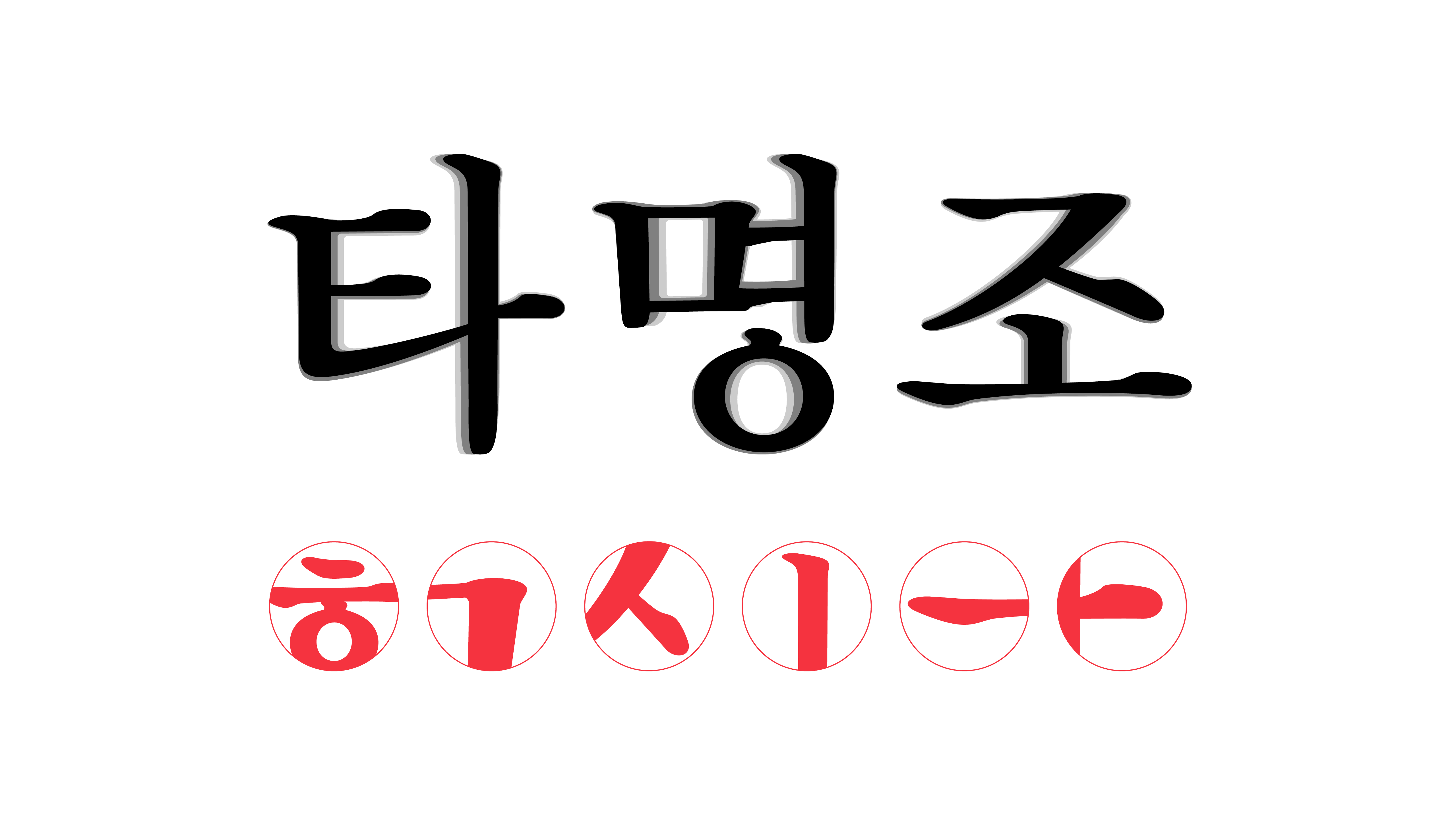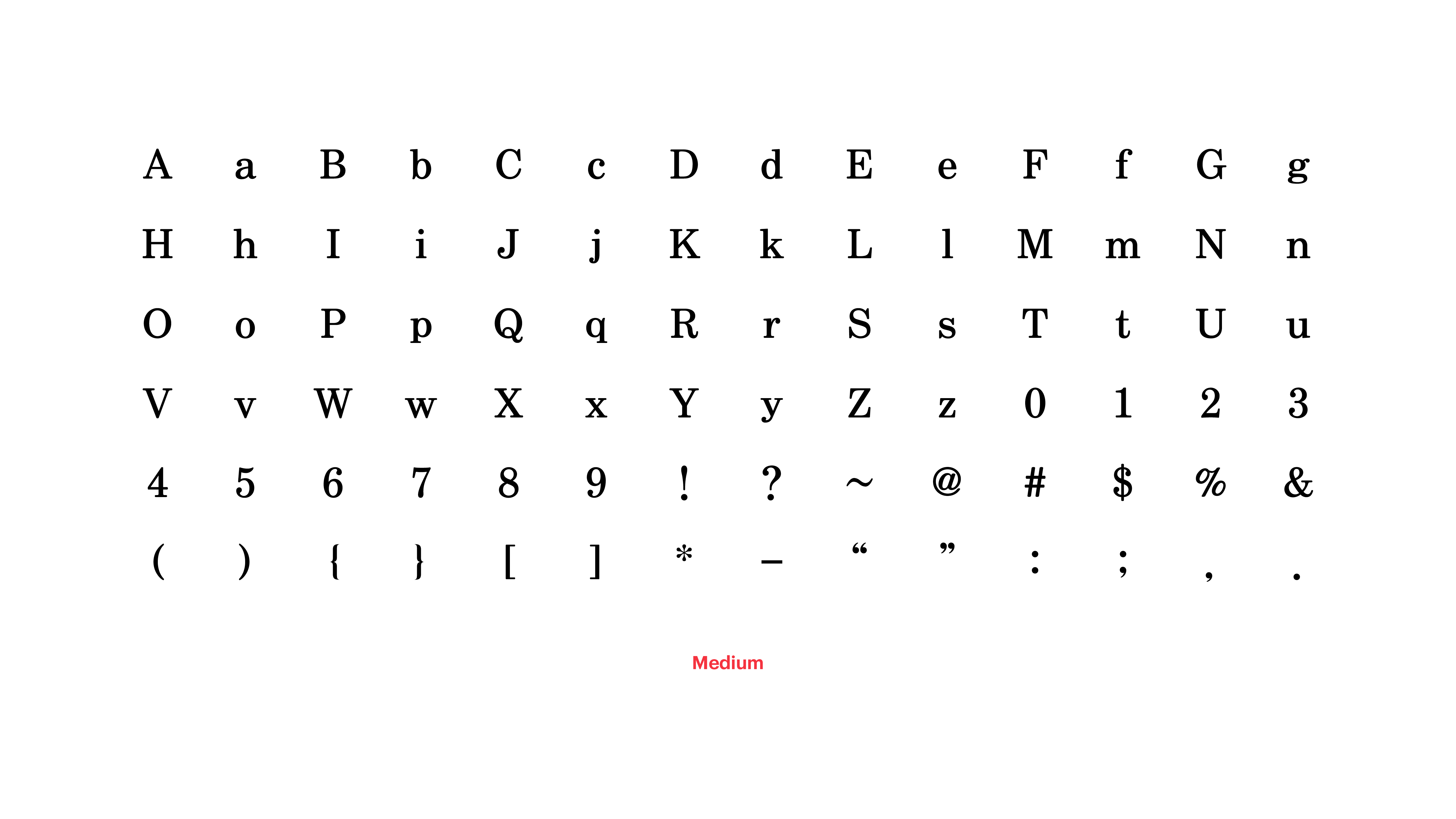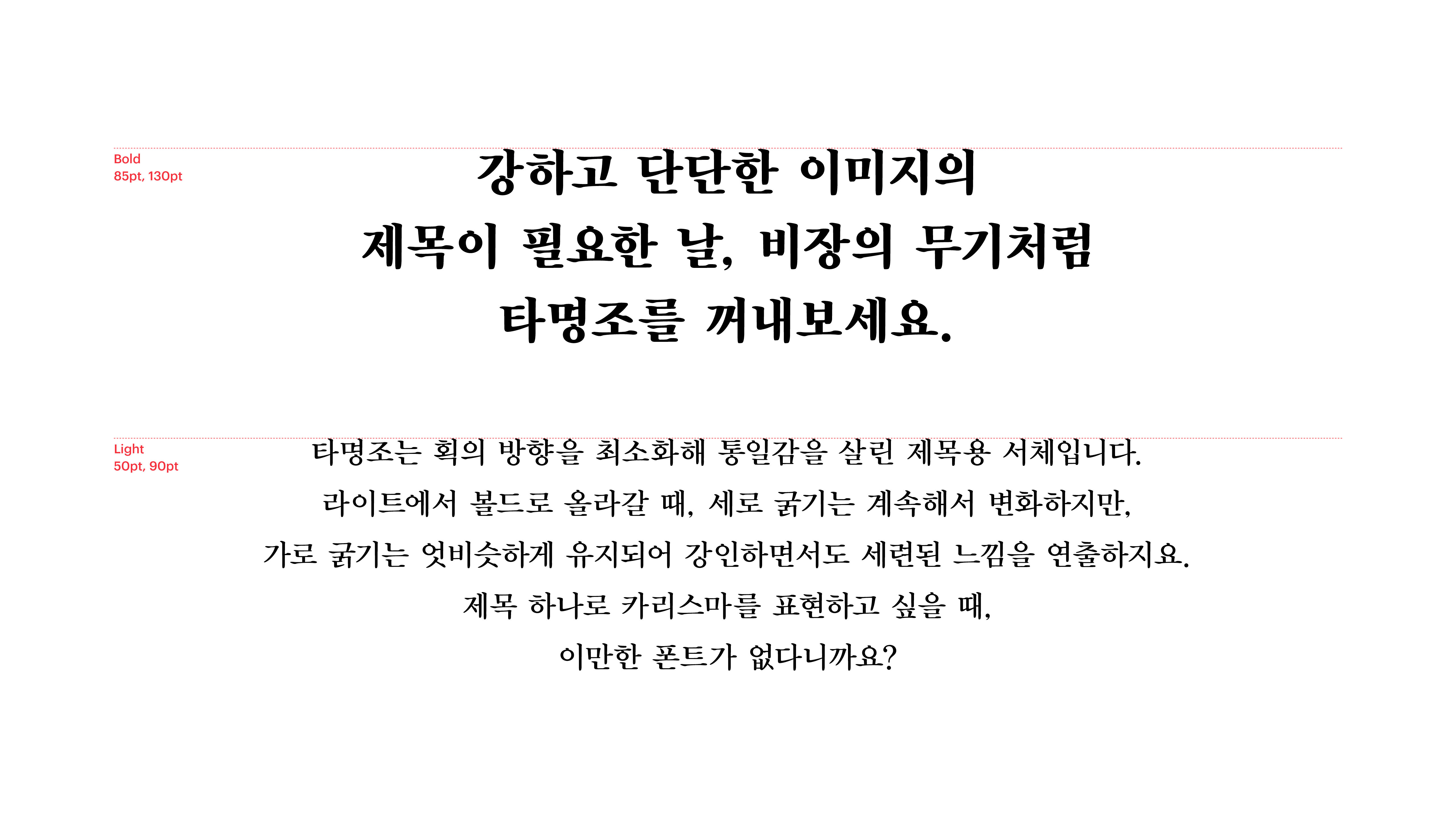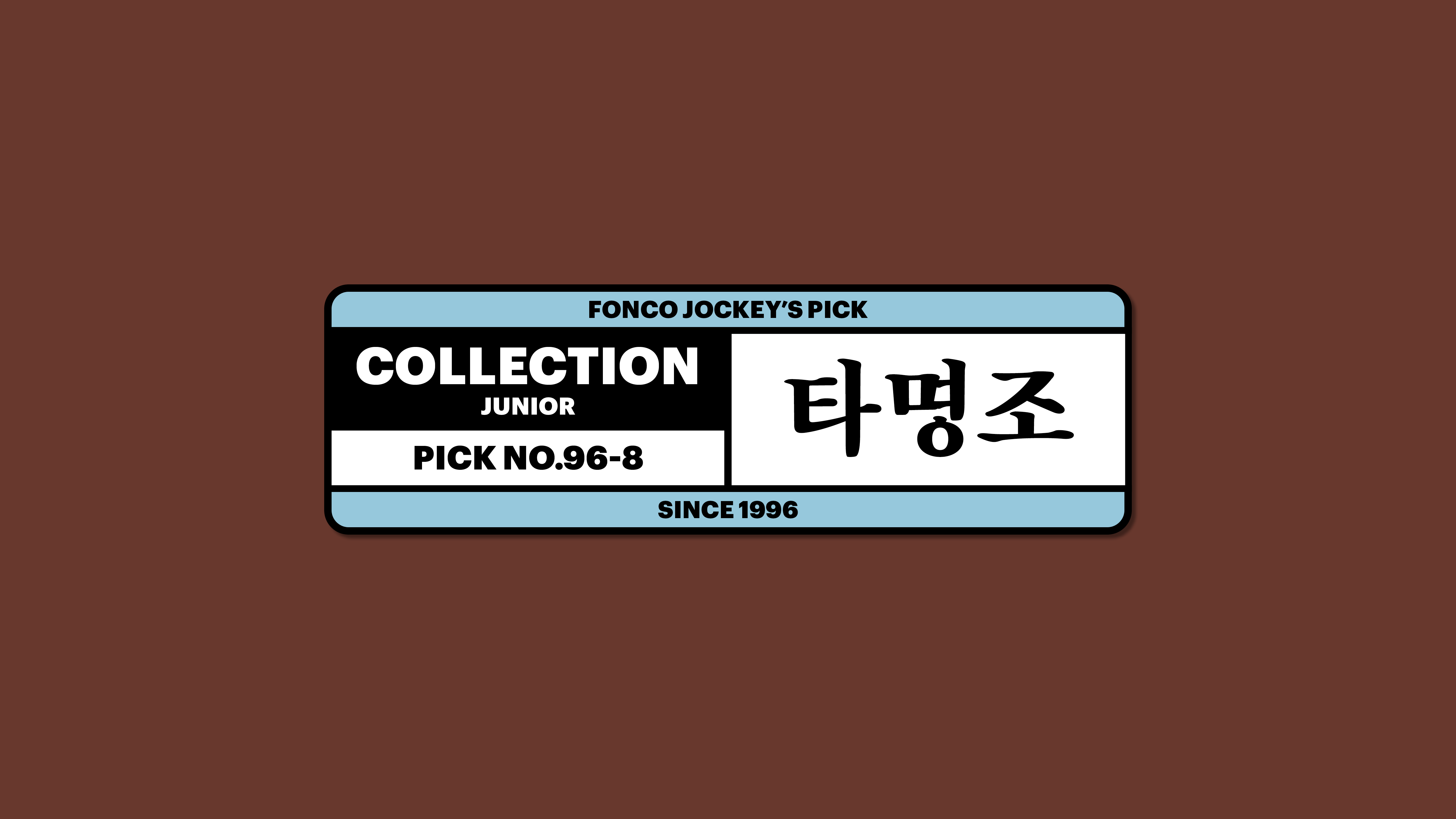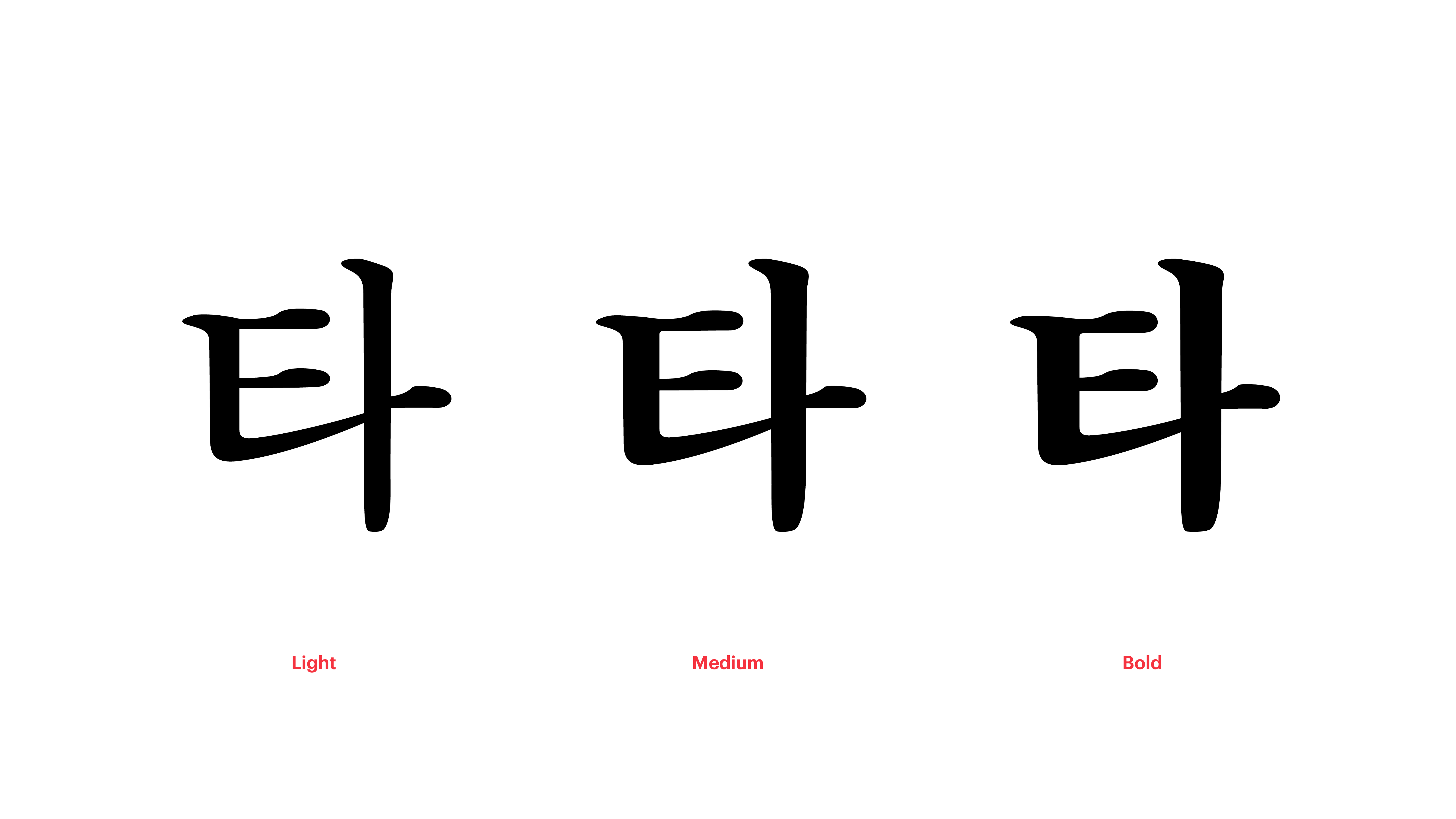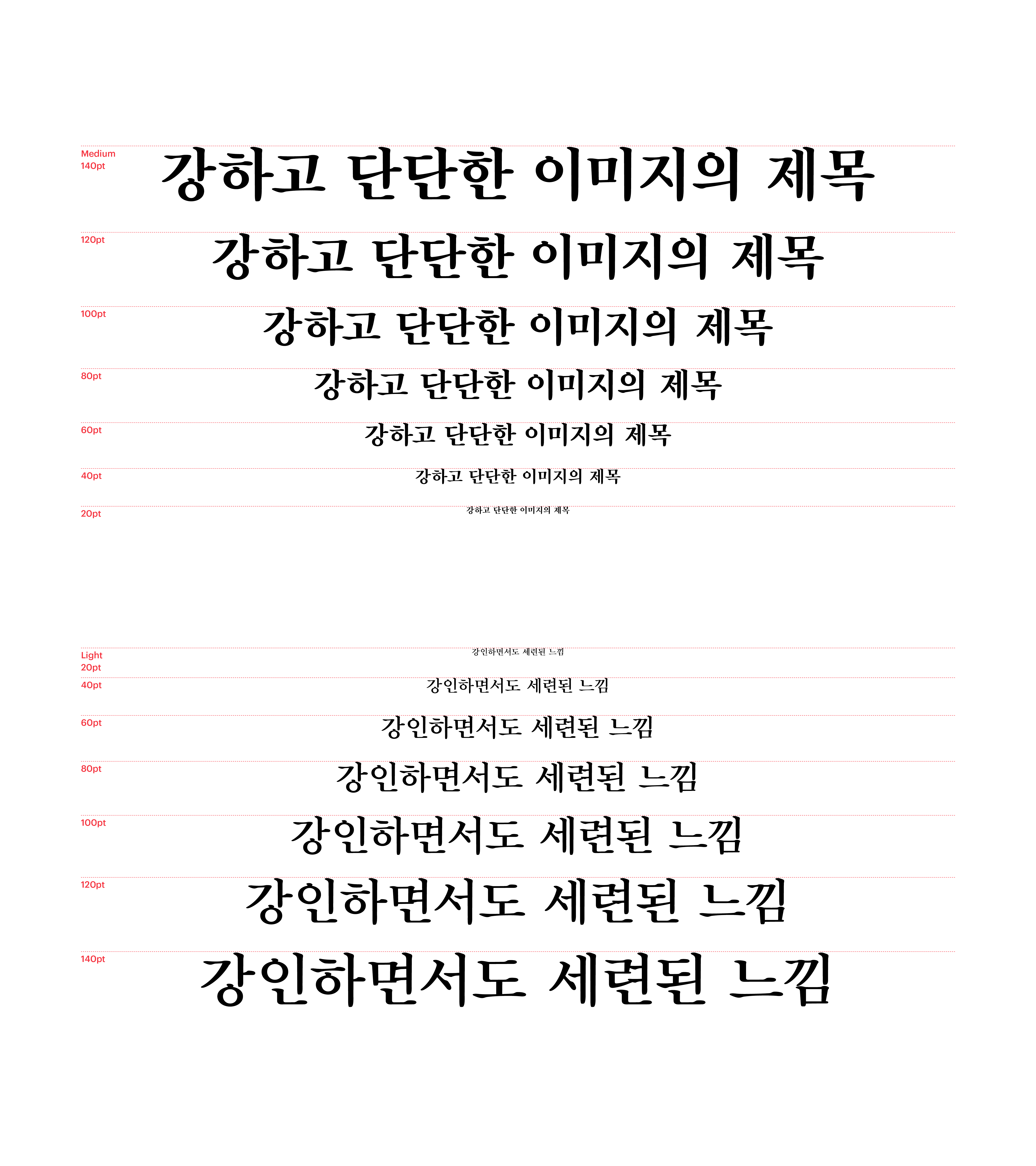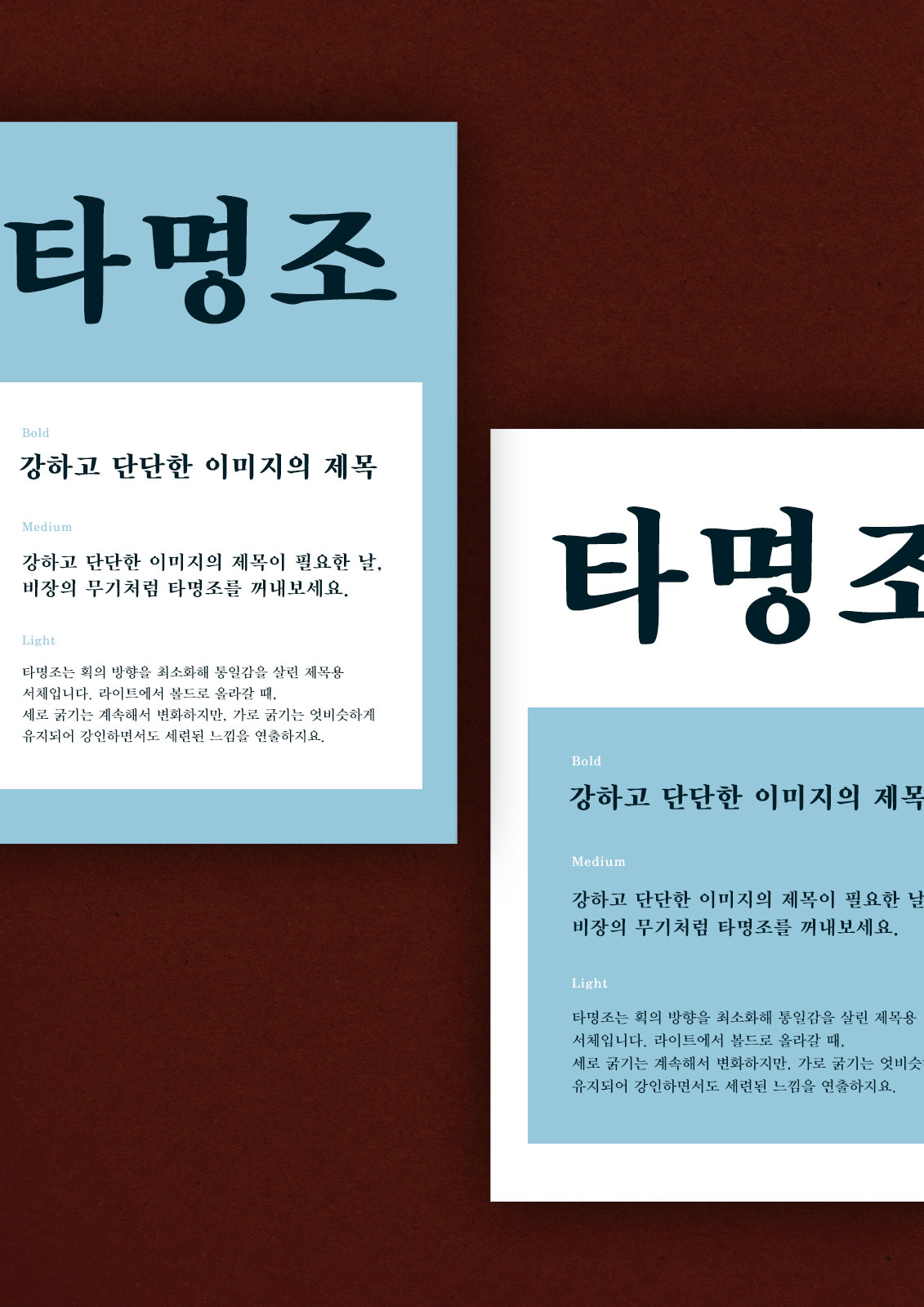
타명조
Yoon 타명조
타명조는 획의 방향을 최소화해 통일감을 살린 제목용 서체입니다. 라이트에서 볼드로 올라갈 때, 세로 굵기는 계속해서 변화하지만, 가로 굵기는 엇비슷하게 유지되어 강인하면서도 세련된 느낌을 연출하지요. 제목 하나로 카리스마를 표현하고 싶을 때, 이만한 폰트가 없다니까요?